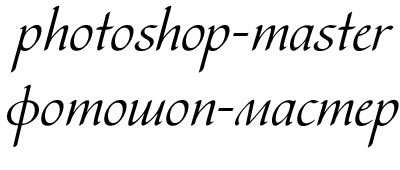
Шрифт отличный, но в нём ошибка одна нашлась! Разработчик не установил украинскую букву "ї" маленькую, вместо неё обычная буква "і" выходит. Очень неудобно потом точки дорисовывать. И, кстати, большая буква как надо с двумя точками. Может кто знает как это исправить или даст ссылку на исправный шрифт?
отличный шрифт)
красивый, аккуратный